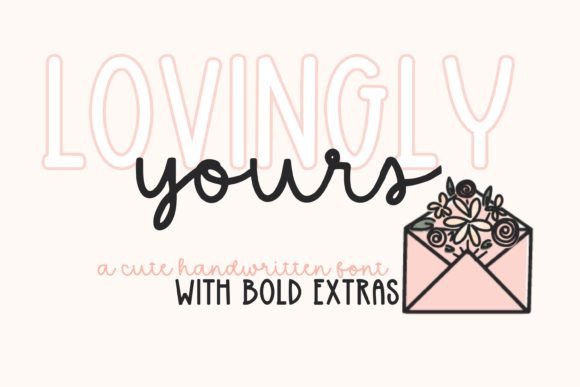
Lovingly Yours
適切なデザイン要素を見つけるのは難しい場合がありますが、Lovingly Yoursは作品を即座に引き立てる優れたコレクションを提供します。
POD(オンデマンド印刷)製品、結婚式の招待状、またはソーシャルメディアのグラフィックを作成している場合でも、Lovingly Yoursは理想的です。